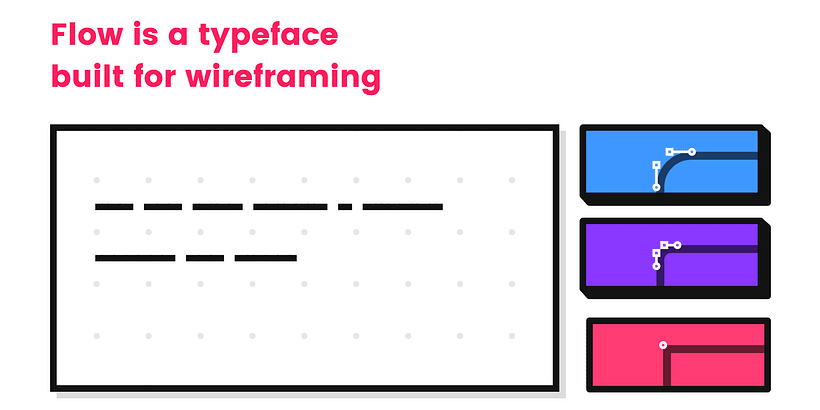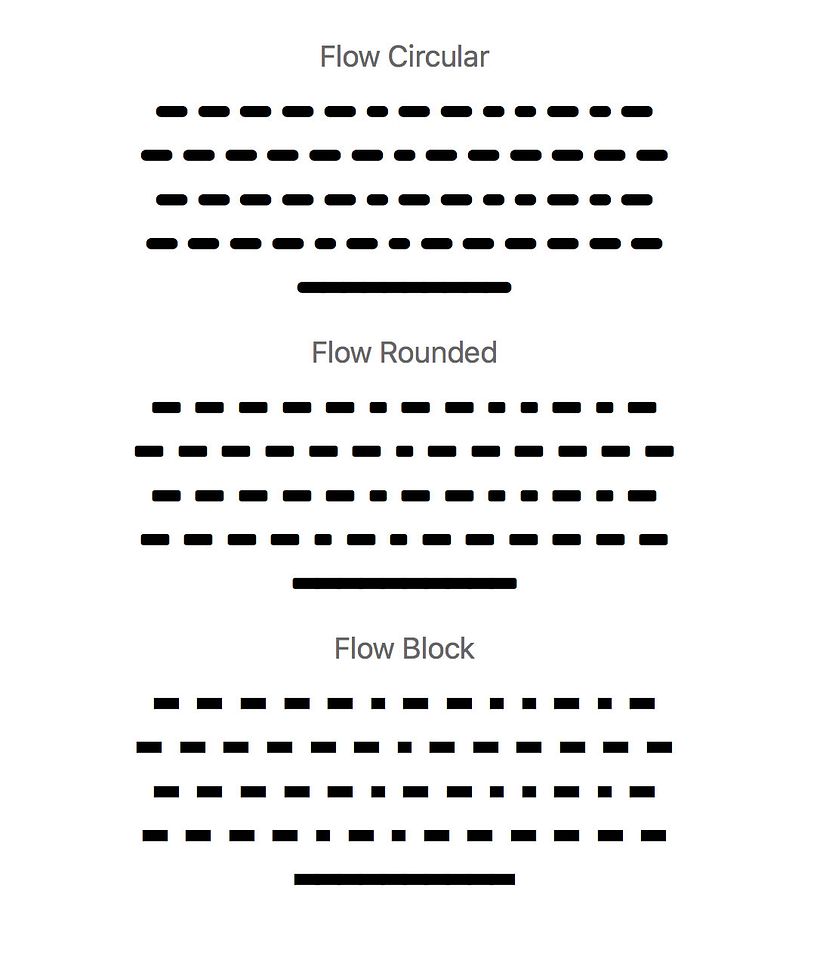
Flow, una tipografía para wireframes
Ya puedes olvidarte del lorem ipsum en tus wireframes, la tipografía Flow es esquemática e ideal para ellos.
Un buen diseño siempre tiene detrás un gran trabajo de esquematización de los contenidos. Plantear la estructura y la composición es esencial, especialmente si hablamos de diseños que deben en cuenta la usabilidad y la accesibilidad. En esos casos el wireframing es imprescindible.
En los planos o esquemas de diseño web o app, casi con total probabilidad, tendrás que incluir bloques de texto y miles de veces habrás recurrido al clásico texto falso o lorem ipsum. De ahora en adelante, no obstante, podrás echar mano de Flow, una topografía pensada especialmente para wireframes, que te permite bocetar tus diseños sin necesidad de prestar especial atención a la composición del texto.
Flow es una tipografía esquemática que viene en tres pesos: circular, redondeada y rectangular, y que puede descargarse en la modalidad pay-what-you-want.